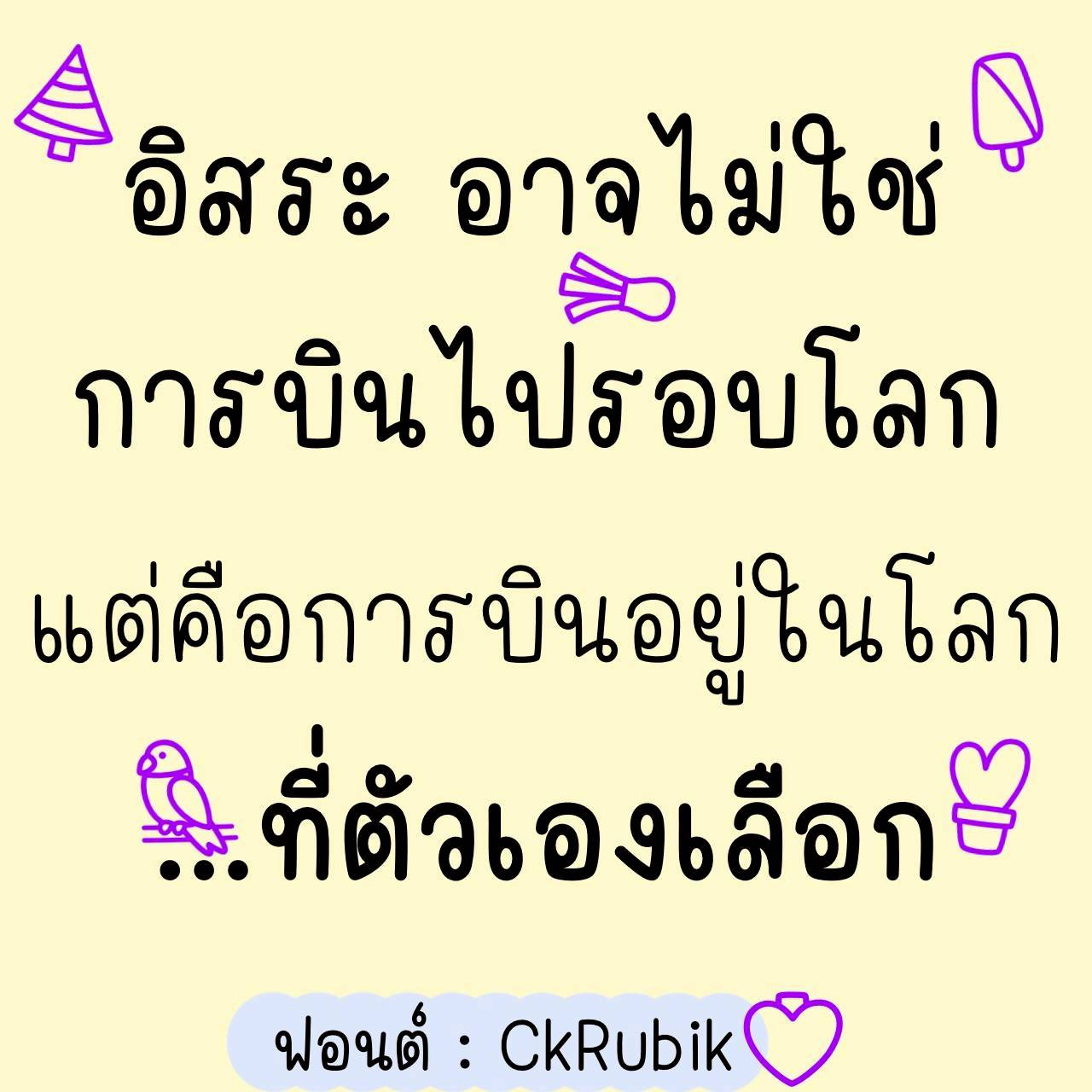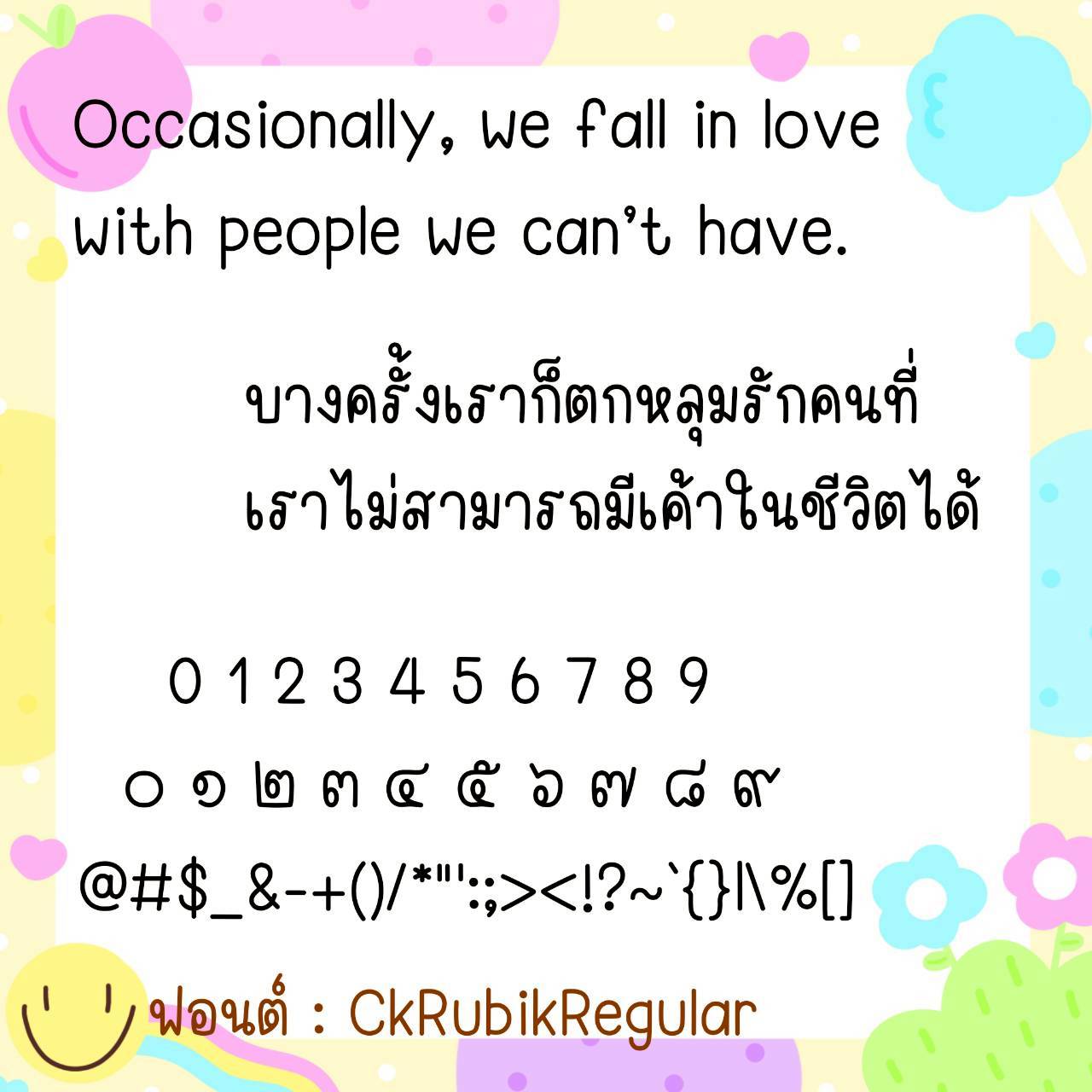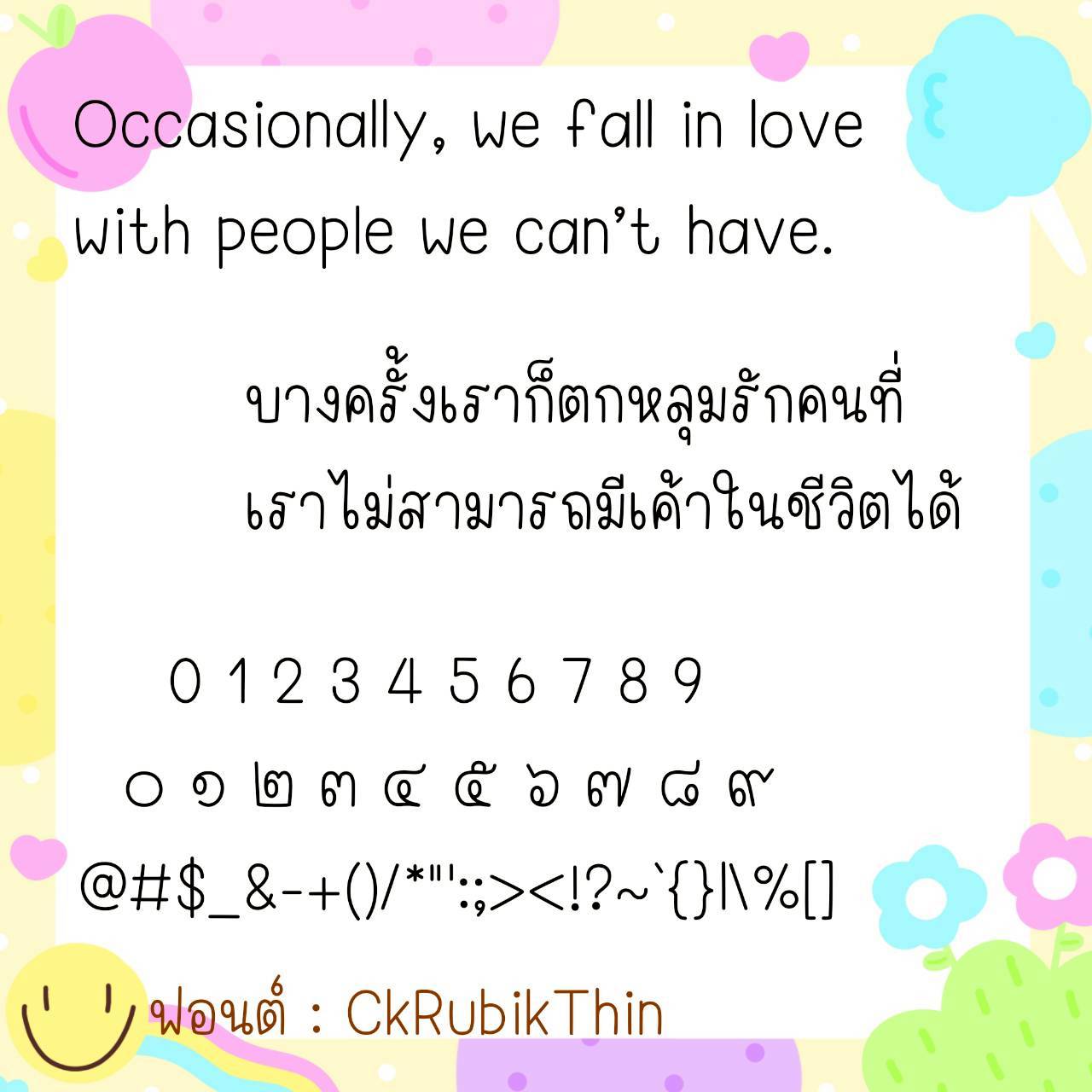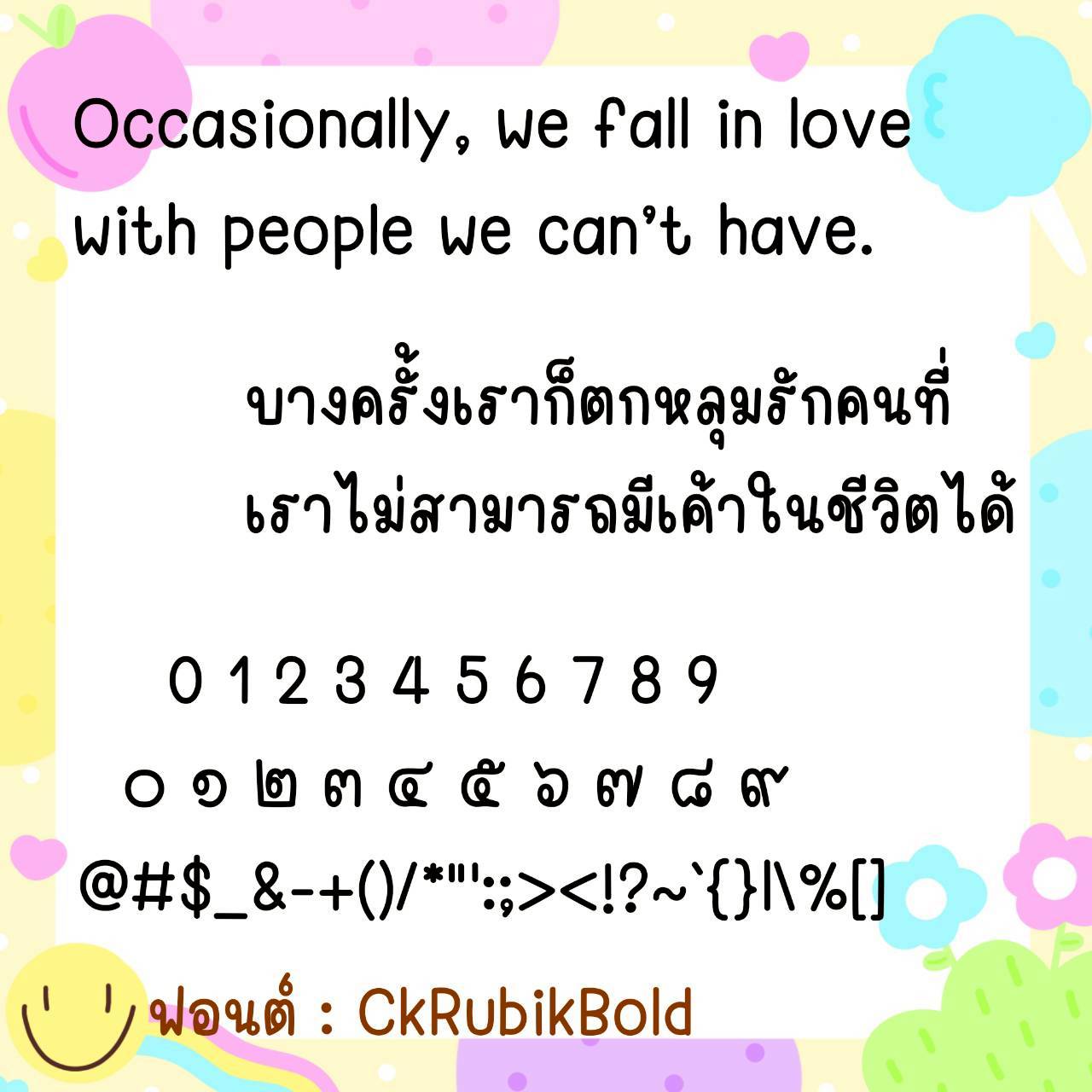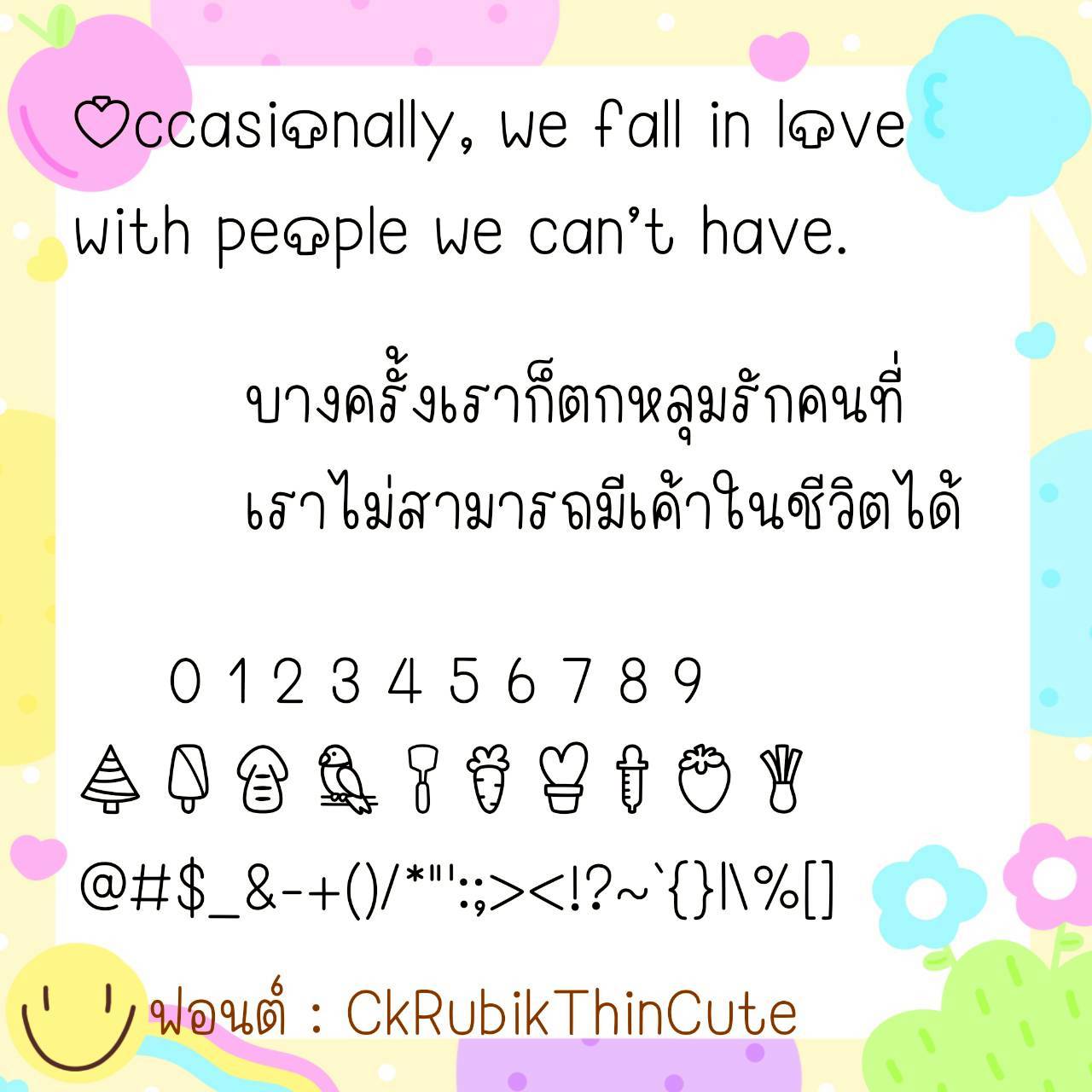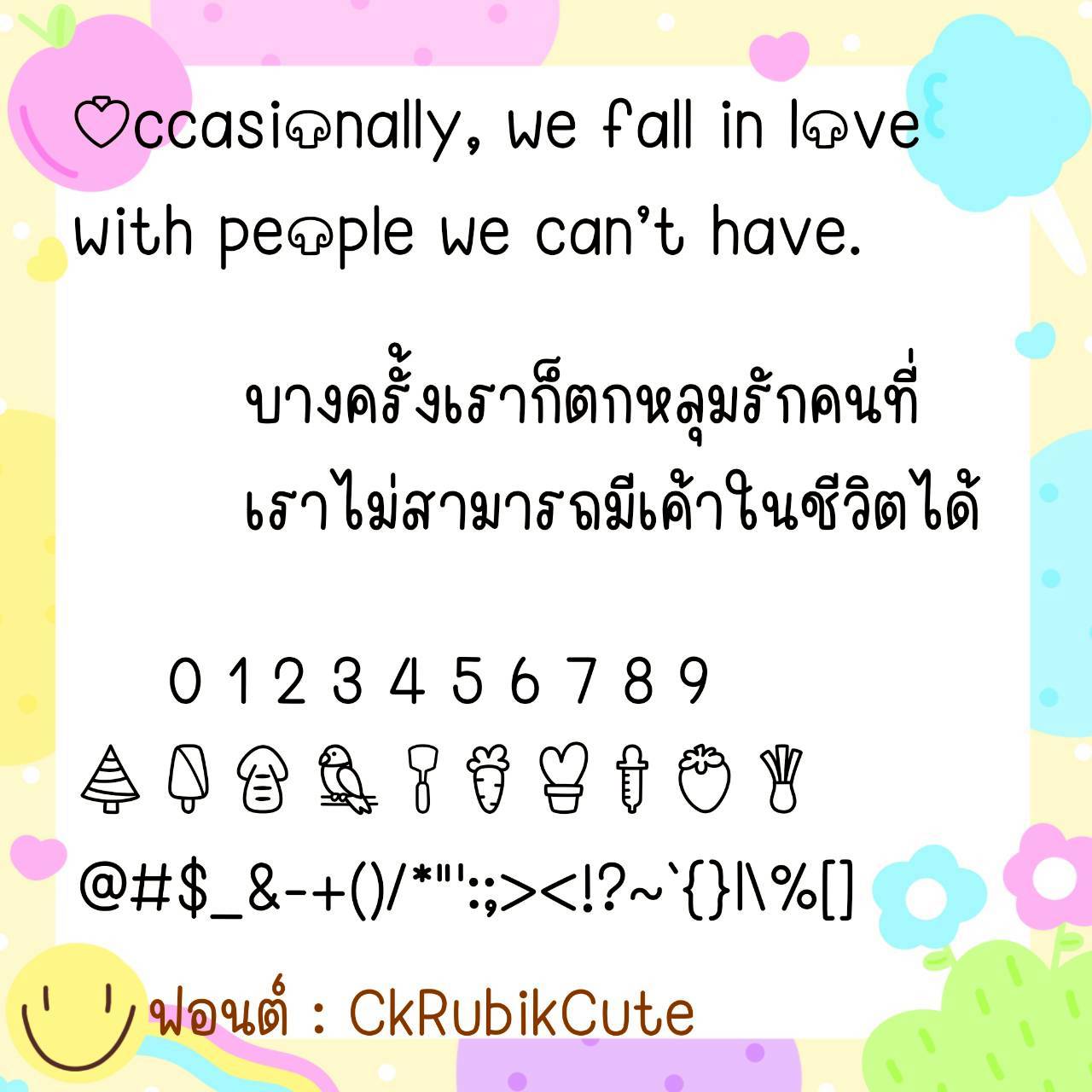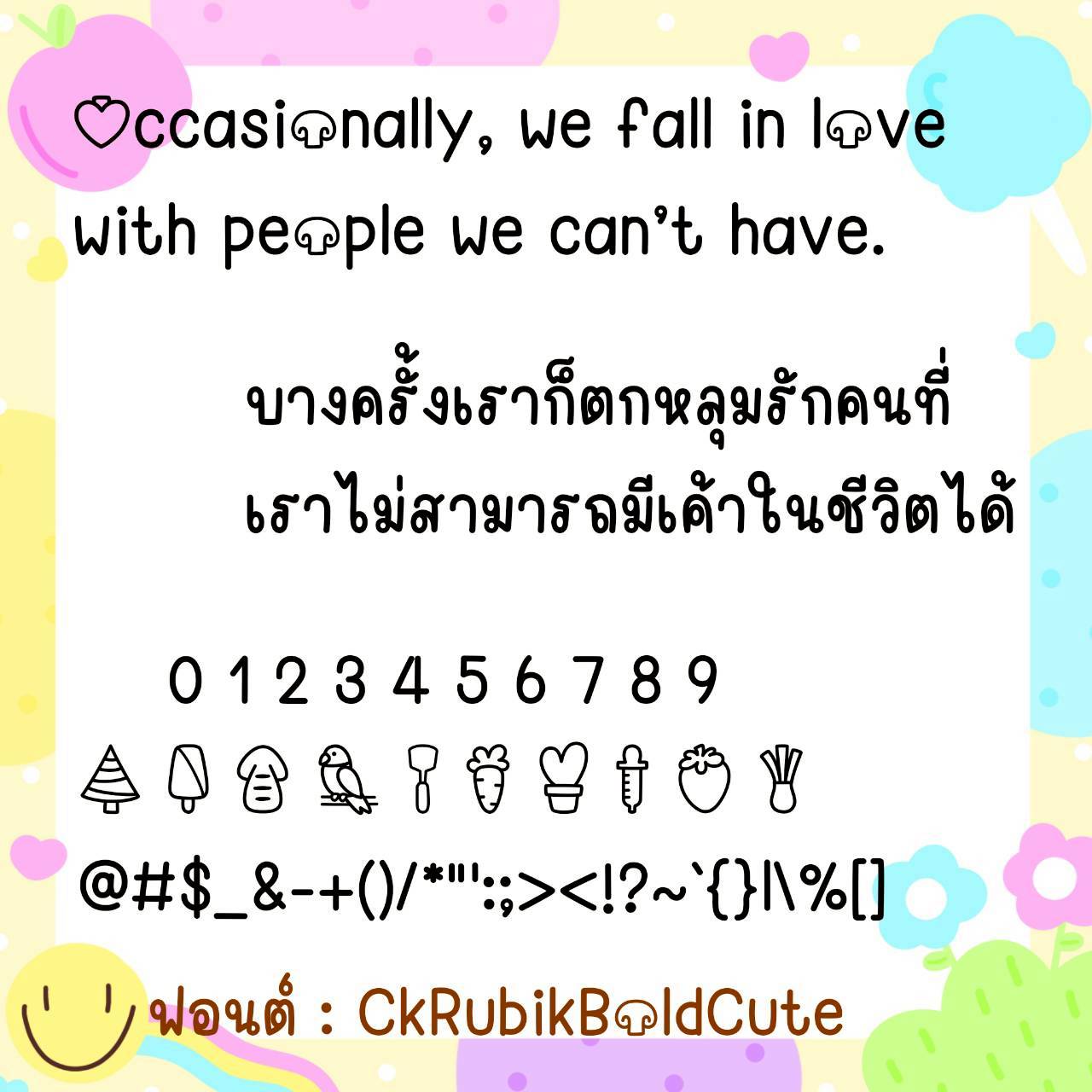
Font CkRubik
ชื่อสินค้า : Font CkRubik 💙
🔸 ฟอนต์ลายมือหัวยาวรีน่ารักแบบวัยรุ่น ขนาดตัวพอดีๆไม่อ้วนไม่ผอมเกินไป ดูเป็นลายมือเขียนหวัดนิดๆ แต่ยังอ่านง่าย และยังมีไฟล์อิโมจิน่ารักๆที่ใช้แทนเลขไทยให้ด้วยค่ะ 🥰💙
🔹 A cute, youthful, long-handled font. The size is just right, not too big or too small. It has a slightly cursive handwriting style, but is still easy to read. It also includes cute emojis that can be used to replace Thai numerals. 🥰💙